ほんとに、フォント。 フォントを活かしたデザインレイアウトの本
デザイン事務所ingectar-e著書による、フォント作例集「ほんとに、フォント。 フォントを活かしたデザインレイアウトの本」がソシムから2019年2月20日に発売された。
「ほんとに、フォント。 フォントを活かしたデザインレイアウトの本」は好評発売中のデザイン書「けっきょく、よはく。 余白を活かしたデザインレイアウトの本」のシリーズ第2弾となる。
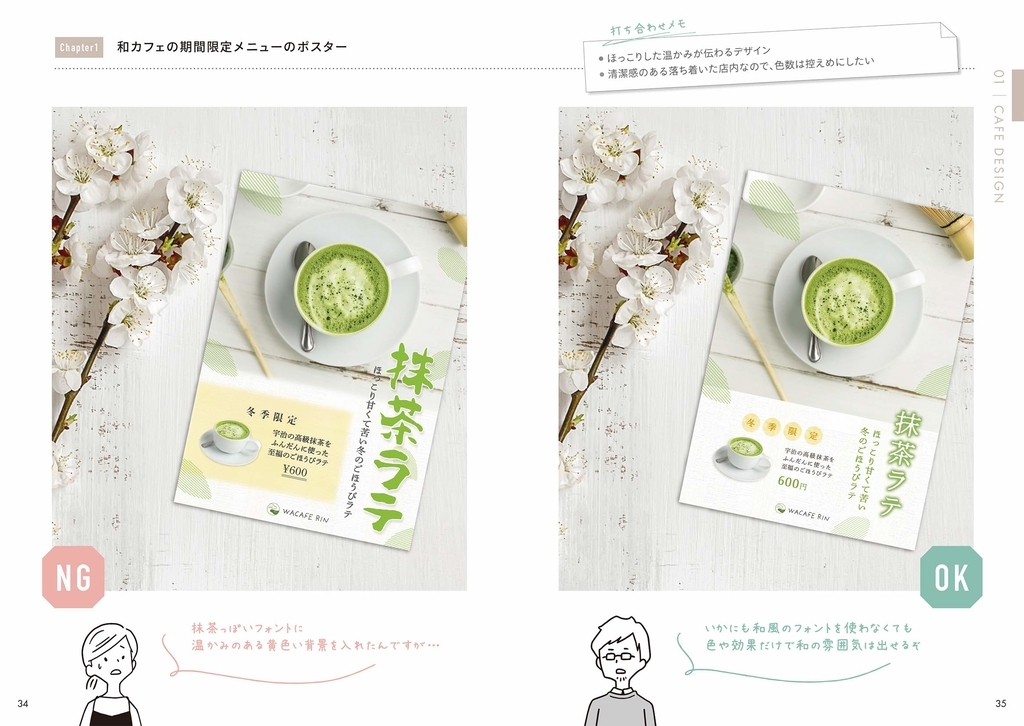
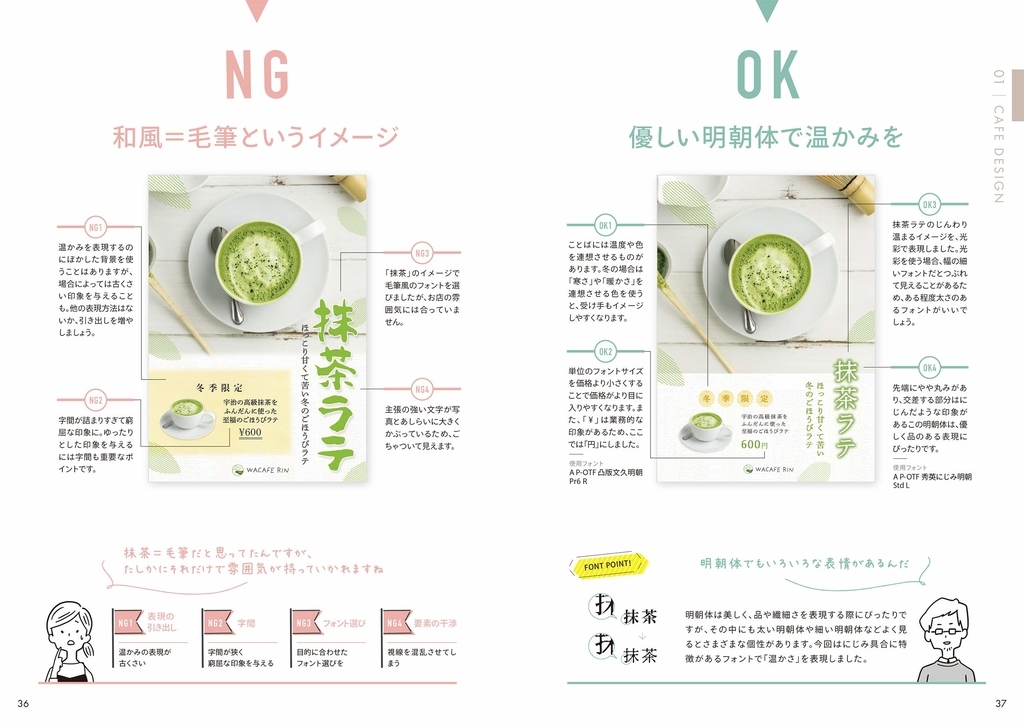
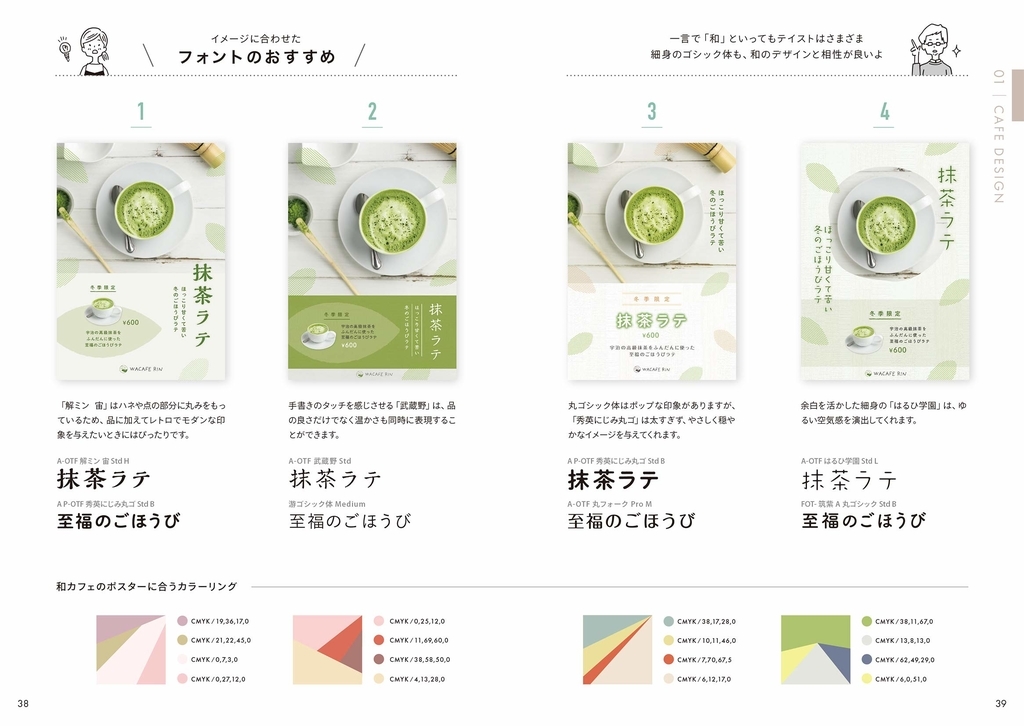
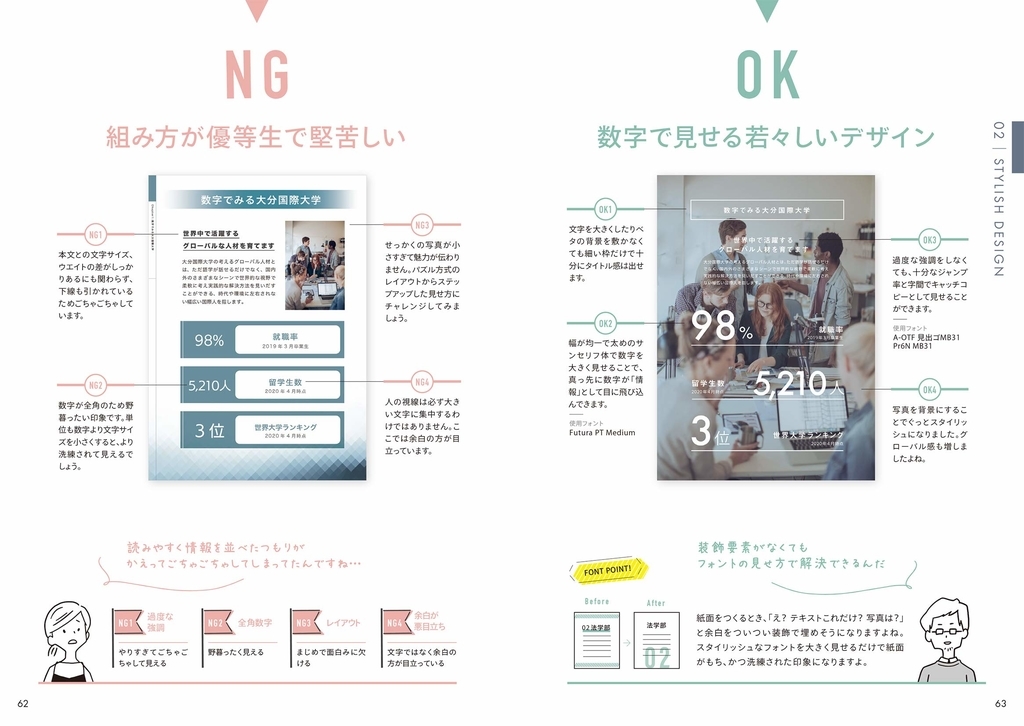
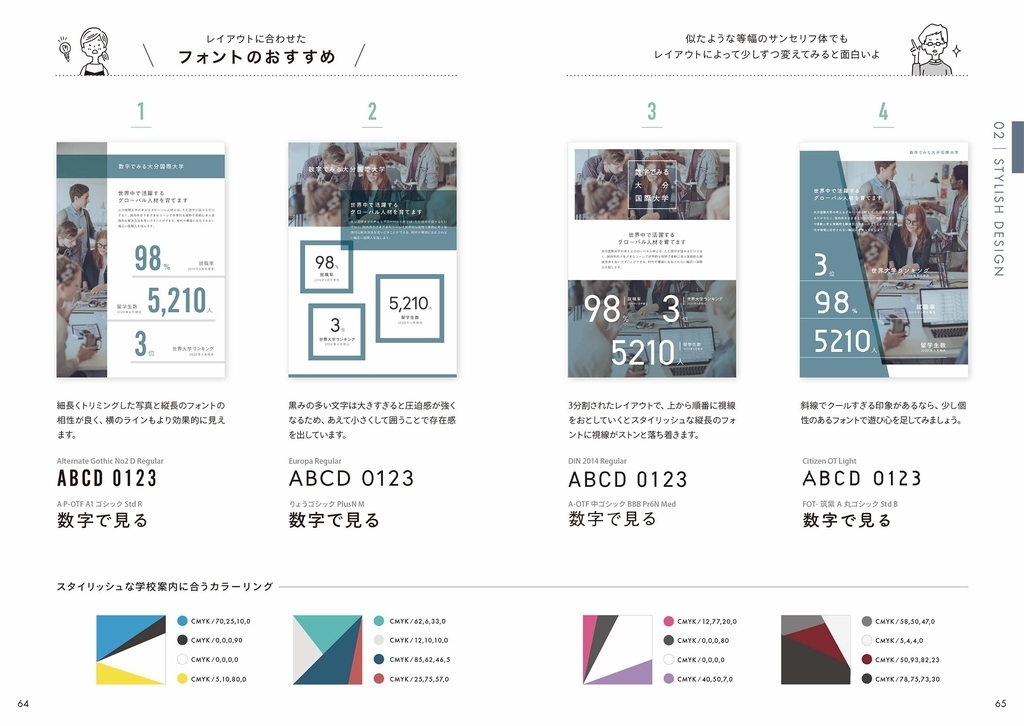
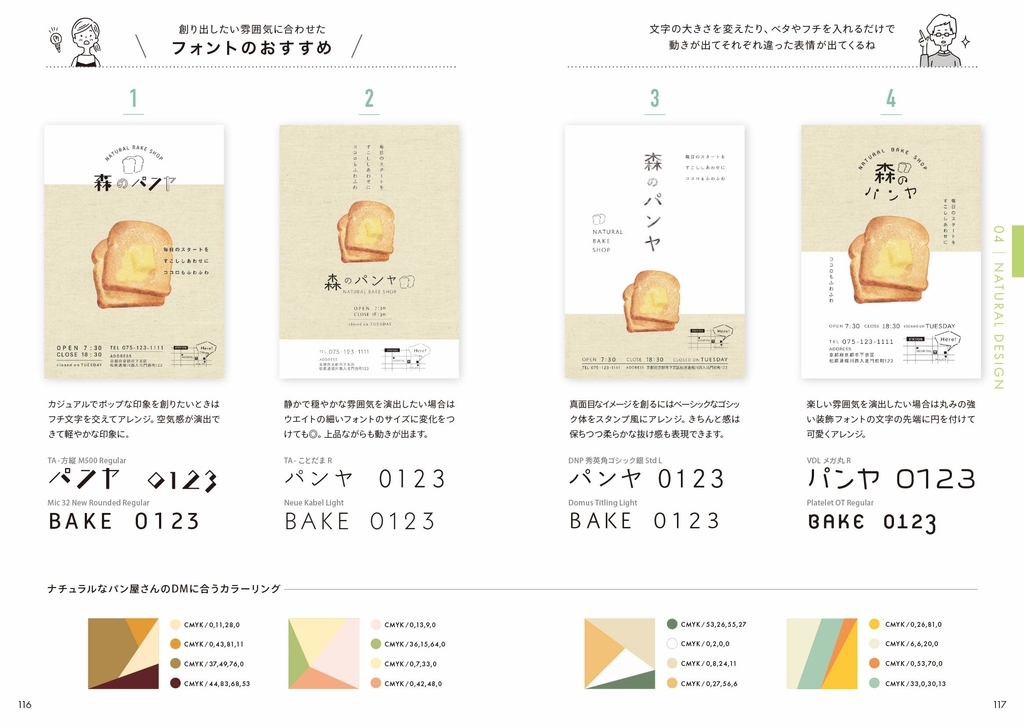
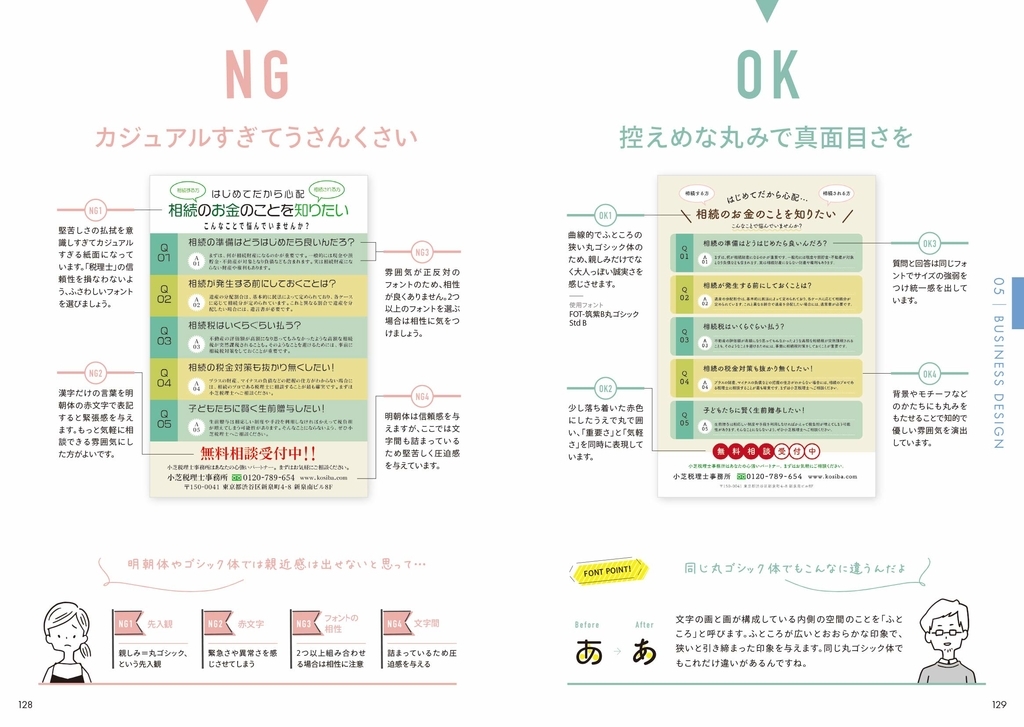
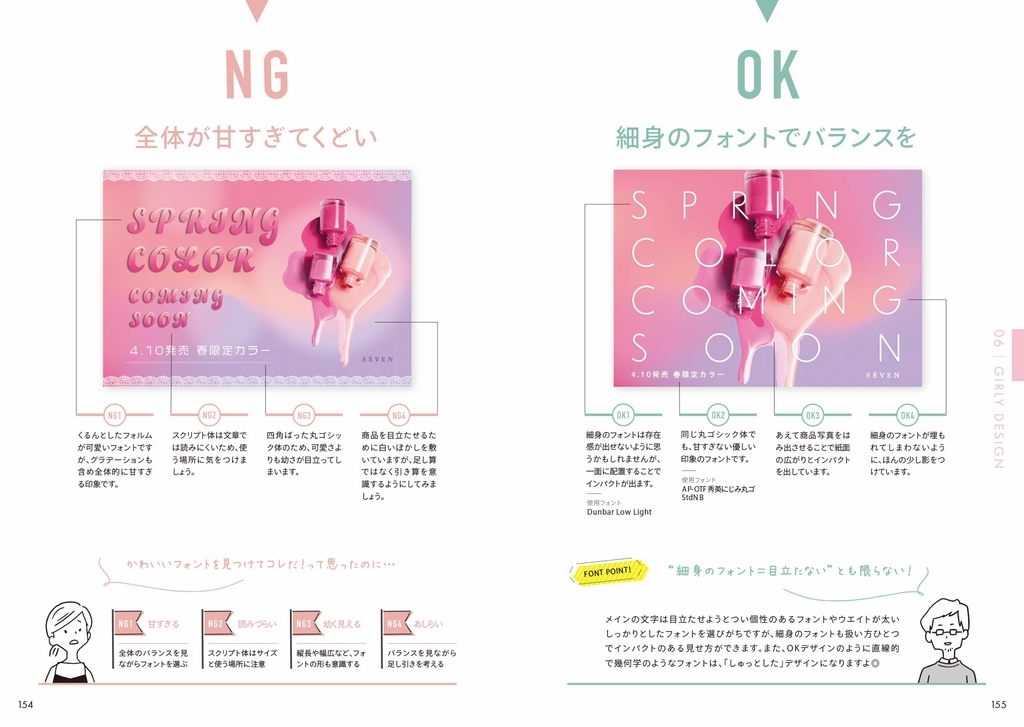
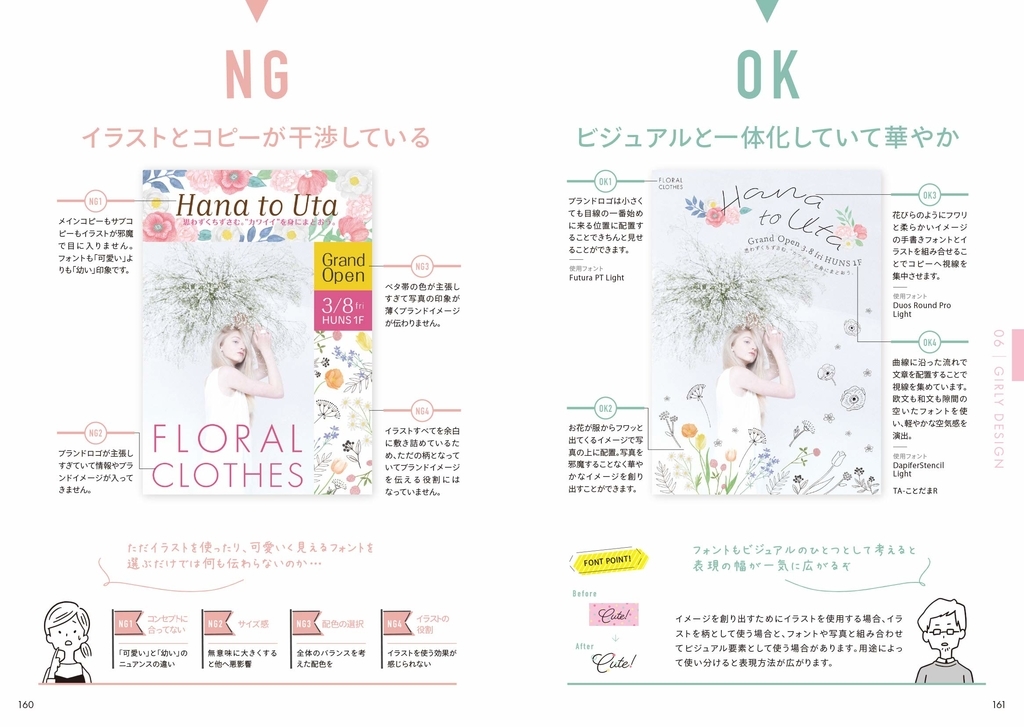
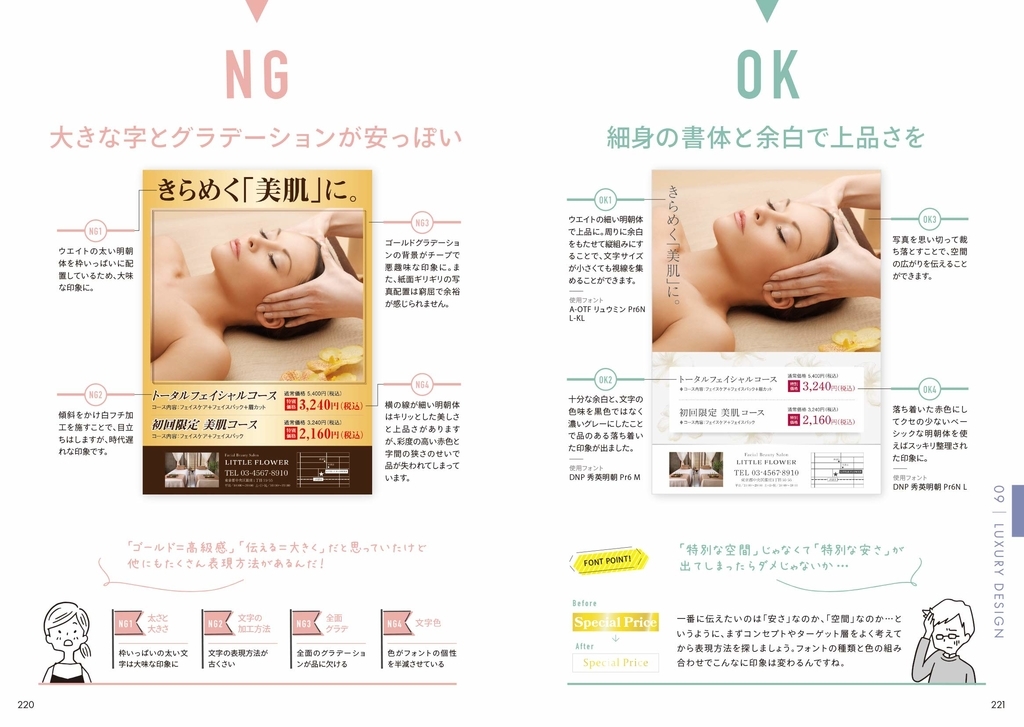
ほんとに、フォント。 フォントを活かしたデザインレイアウトの本
こんどは「フォント」でデザインをおしゃれに変える!
フォントの知識を深める専門書は数あれど、
結局、どのフォントをどう使えばいいの?
に答えてくれるものはありません。
フォント使いのコツ? ルール? 必殺技?
残念ながら…そんなものはありません。
フォント選び、それは"センス"。
もちろんそのフォントを選んだ理由は必要です。
クライアントを納得させるためには知識も必要でしょう。
でも実際にデザインするときは…
「ターゲットの年齢層が高めだから落ち着いた明朝体、
可読性を上げるためにウエイトは太めがいいかな…」
↑↑↑
ここからはじまって、
「じゃあ、条件に合うフォントは…」
↑↑↑
ここにセンスが必要!!
つまり、
フォントが変わればデザインは変わる!
そして、フォントのセンスを磨くにはたくさんの使用例を見ることが大切です。
本書はその経験値を上げるための作例集です。